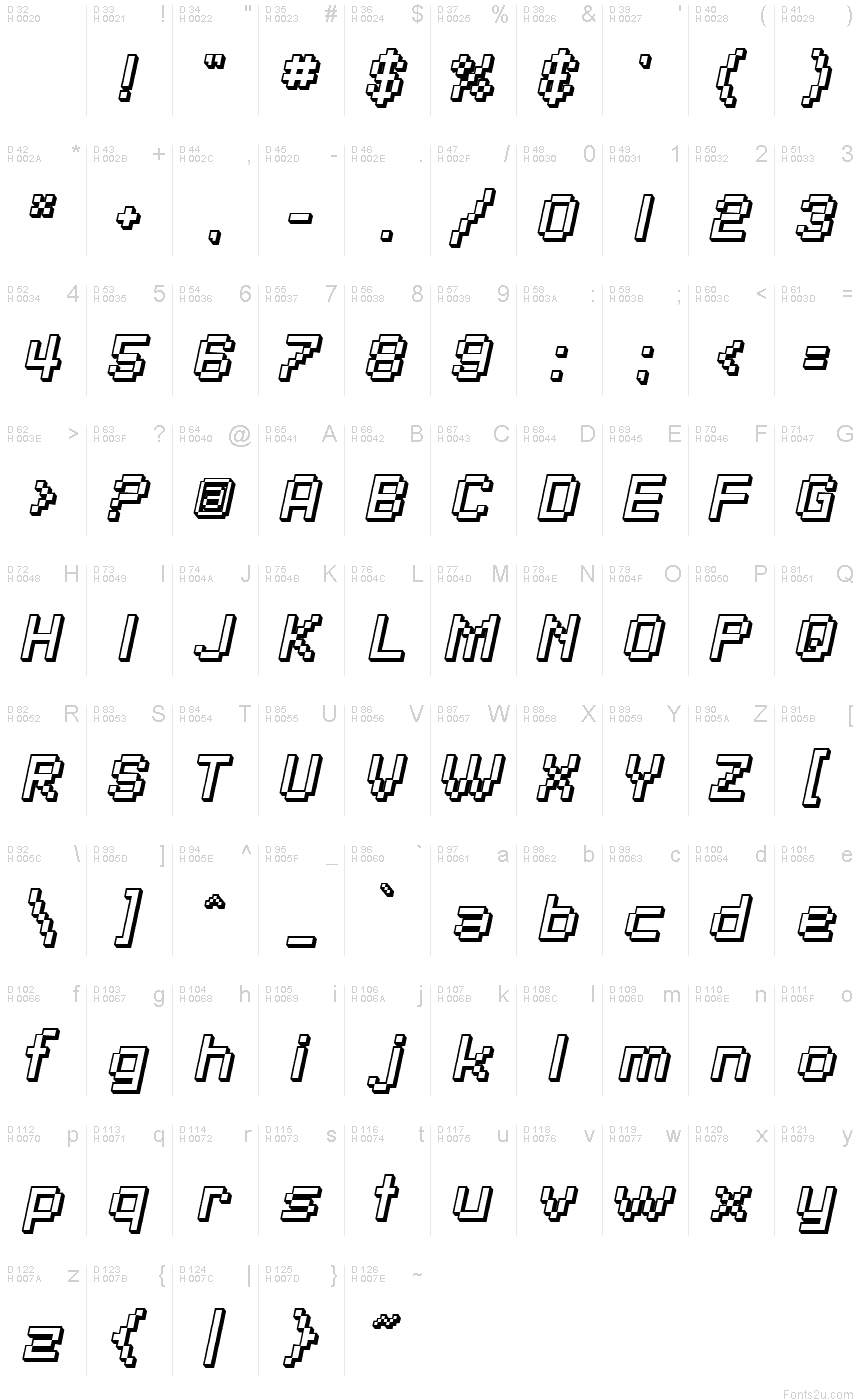
SF Pixelate Shaded Oblique di ShyFoundry è un font display pixel gratuito con una struttura solida e inclinata e un audace effetto ombra 3D. Le lettere sembrano prese direttamente dalla grafica arcade e dalla tipografia dei primi schermi: angoli squadrati, diagonali a gradini e un offset nero che dona al design quel tocco deciso dell'era videoludica.
Si adatta perfettamente a poster di giochi retro, copertine di album synth-heavy, streaming overlay, fanzine e titoli, laddove serva una resa che richiami subito l'atmosfera digitale. Essendo un font gratuito, funziona bene anche per badge, bozze di loghi e titoli compatti, poiché il trattamento in ombra inclinata conferisce anche alle scritte brevi una forte spinta direzionale.